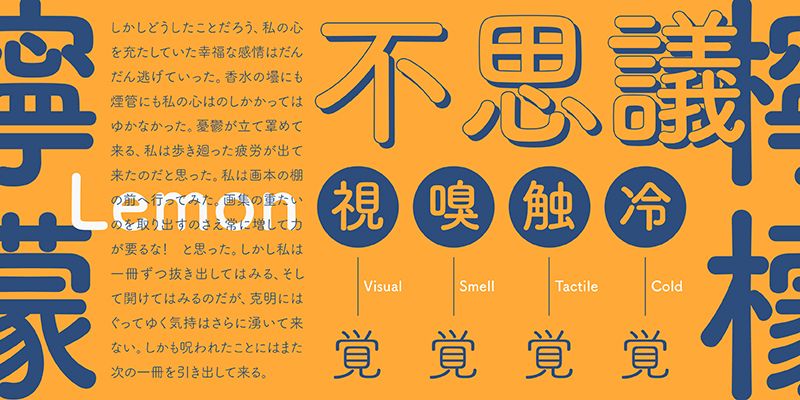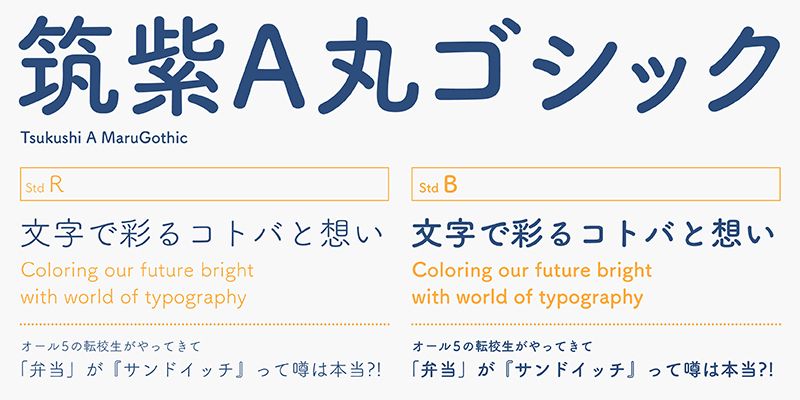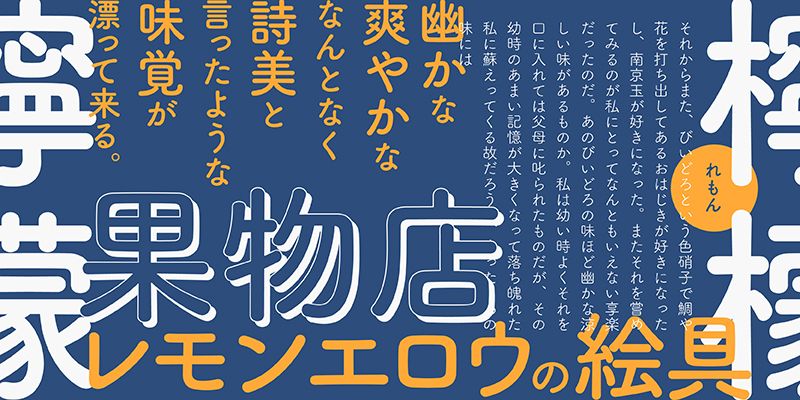
FOT-TsukuARdGothic Std unterscheidet sich deutlich von gewöhnlichen gotischen Rundschriften (ohne Serifen). Es handelt sich um eine runde gotische (serifenlose) Schrift mit modernem Charakter. Im Gegensatz zu vielen anderen modernen Designs, die größere Zwischenräume haben, hat die FOT-TsukuARdGothic Std jedoch engere, kleinere Zwischenräume. Die Kanji-Zeichen (ideografische Zeichen) haben Striche mit abgerundeten Kanten und sanften Kurven anstelle von geometrischen Formen und geraden Linien, was ein warmes Gefühl vermittelt. Die syllabischen Kana-Zeichen sind in einem neutralen Design gehalten. Mit FOT-TsukuARdGothic Std können Sie besonders gute Satzergebnisse erzielen.
(Der Buchstabe „A” oder „B” in jedem Schriftnamen steht für ein anderes Design der Kana-Zeichen. Die Kanji und andere Zeichen werden von beiden Schriftarten gemeinsam verwendet).